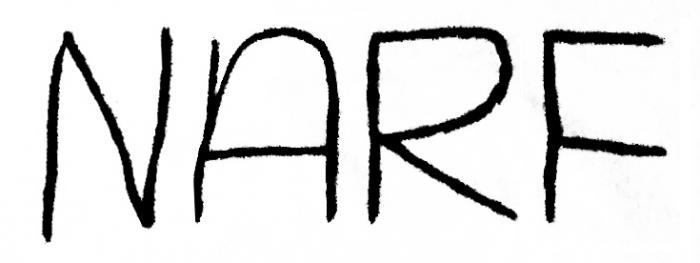
Suche diese oder ähnliche Schrift
Ich habe vor ca einem Jahr mal meiner Schwester ein T-Shirt gemalt und dann auf irgendeiner Schriften-Seite diese Schrift gefunden. Nun wüsste ich gerne, wie diese Schrift hieß, weil ich sie eigentlich doch ziemlich hübsch finde, kann sie nur dummerweise auch trotz langer Suche nicht mehr finden.
Leider habe ich als Schriftbeispiel auch nur diese vier Buchstaben, das ist nicht viel, ich weiß.
Aber da das A ja eine etwas ungewöhnliche Form hat, habe ich doch Hoffnung und eine andere mit ähnlichem Erscheinungsbild wäre ja auch vollkommen okay.
Lad dein Bild mal hier: http://www.whatfontis.com hoch, da bekommst du genügend ähnliche angezeigt. Oder schau bei dafont.com, da gibt’s sicher reichlich Mundgebissenes.
Hab es schon mit whatfontis.com und ähnlichen Seiten versucht, aber dort keine gefunden, die mir wirklich gefallen hat...
Und auf dafont hab ich auch schon vorbei geschaut (denke auch, dass ich sie damals daher hatte), aber auch dort ist mir bisher nichts entgegen gekommen, was mich wirklich glücklich macht...
Ich finde kaum eine Schrift, die dieses R hat. Ich mag die Proportionen der Schrift total und das Aussehen des Rs halt vor allem. Nur wenn das R passt, dann sieht das A so richtig doof aus, oder aber das F. Zu jedem einzelnen Buchstaben allein hab ich ne passende Schrift, aber halt keine, bei der mir alle  gleichzeitig gefallen...